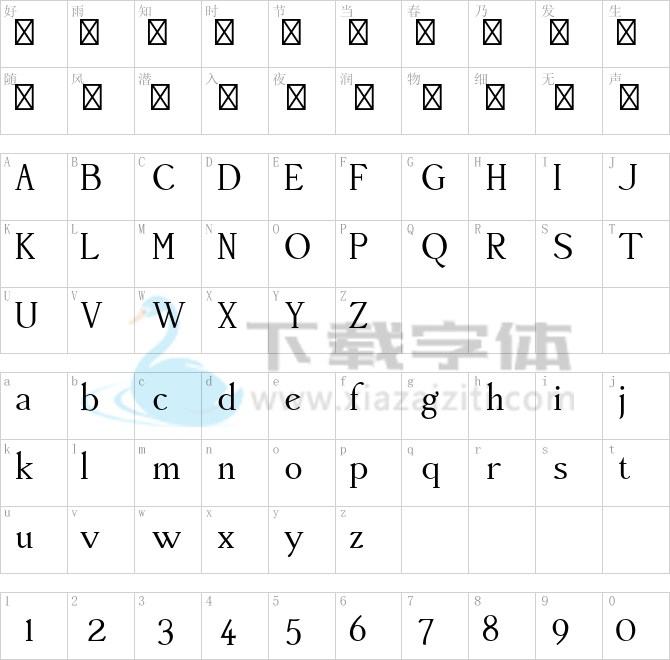
Accanthis ADF Std No2.otf字体下载,这款字体结构工整、笔画清晰,兼顾美观与易读性,适用于标题、正文、海报、包装、LOGO 等多种场景。字形优雅稳定,风格百搭耐看,适配日常排版与创意设计,让文字呈现更舒适、更具质感。Accanthis ADF Std No2.otf字体下载一笔一画,皆是细节,以均衡的比例、流畅的线条打造舒适视觉体验,字形端正大气,风格简约现代。无论是商业设计、品牌宣传还是日常排版,都能轻松驾驭,让文字更有格调与力量。Accanthis ADF Std No2.otf字体下载字体下载。